15 лучших программных шрифтов для лучшего кодирования
Опубликовано: 2022-03-11У вас напряжение глаз или трудности с чтением кода после нескольких часов напряженной работы? Многие программисты никогда не думают о смене шрифта до тех пор, пока у них не начнутся головные боли.
Если вы часто замечаете, что ваши глаза затуманиваются при попытке отсканировать тысячу строк кода или у вас болит голова через несколько часов после того, как вы перестали программировать, возможно, пришло время попробовать новый шрифт. Даже если у вас нет этих симптомов, хорошо продуманный шрифт часто обеспечивает лучшую читабельность по сравнению со стандартными системными шрифтами.
Хотите немного все перемешать? Многие из этих шрифтов бесплатны, поэтому попробовать не помешает. Вот лучшие шрифты для программирования, которые снижают нагрузку на глаза и улучшают читаемость, как бесплатные, так и платные.
Зачем менять программный шрифт?
IDE и инструменты разработчика не всегда поставляются с лучшим шрифтом. Обычно они используют моноширинный системный шрифт, и, хотя для некоторых он может работать нормально, другие сообщают о усталости глаз или плохой читаемости.
Хотя большинство этих программ предлагают возможность переключения шрифтов, многие люди не пользуются ею. Некоторые программисты могут даже не осознавать, что используют некачественный шрифт, пока не переключатся на альтернативу, поддерживаемую сообществом, и не поймут, насколько лучше все может быть.
Хороший шрифт может свести к минимуму головную боль, облегчить сканирование кода и даже кардинально изменить то, как вы работаете.
Так что же такое подходящий программный шрифт? Вот на что вам нужно обратить внимание.
- Четкие и легко читаемые символы снижают нагрузку на глаза, когда вы часами просматриваете сотни строк кода.
- Делает четкое различие между часто путаемыми символами, такими как буква «О» и цифра «0» или строчная буква «L» и цифра «1».
- Лигатуры или дополнительные пробелы для часто используемых символов в популярных языках программирования — не для всех, но другим это нравится.
- Шрифты с несколькими вариациями обработки определенных символов великолепны, поэтому вы можете выбирать именно ту версию, которая вам больше нравится.
Многие программисты предпочитают моноширинные шрифты/шрифты фиксированной ширины, чтобы улучшить читаемость и облегчить поиск ошибок в коде, поэтому большинство из них подпадают под эту категорию. Некоторые из них содержат стандартные, немоноширинные версии в комплекте, если вы так предпочитаете.
Бесплатные шрифты для программирования
В духе открытого исходного кода многие дизайнеры бесплатно выпускают свои программные шрифты, многие из них на таких сайтах, как GitHub. Сообщество любит и рекомендует эти шрифты, поэтому не стесняйтесь загружать их и проверять.
1. Кодекс Фиры
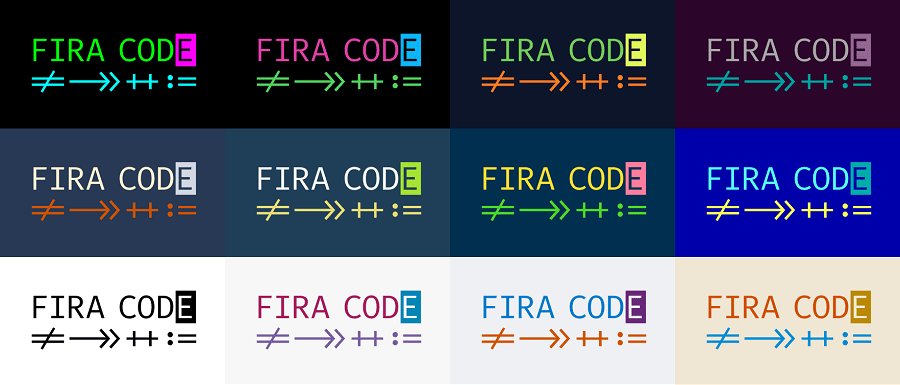
Концепция Fira Code проста: моноширинный шрифт предназначен для объединения часто используемых последовательностей из нескольких символов в одну, что сокращает время, необходимое для сканирования кода и поиска того, что вы ищете.
Например, символ «не равно» (!=) превращается в один символ «равно» с перечеркнутой косой чертой, открывающий и закрывающий символы в HTML (</) располагаются ближе друг к другу и т. д. Эти лигатуры существуют для многих языков программирования.
И это не меняет ни одного из базовых символов, как они выглядят, так что это не повлияет на ваш код. Это просто облегчает чтение!
Есть также несколько вариантов символов, поэтому вы можете настроить шрифт так, как вам нравится.
Fira Code поддерживается большинством браузеров, и вы можете увидеть, как он выглядит на реальных примерах кода, которые они предоставляют.
2. Прогги-шрифты
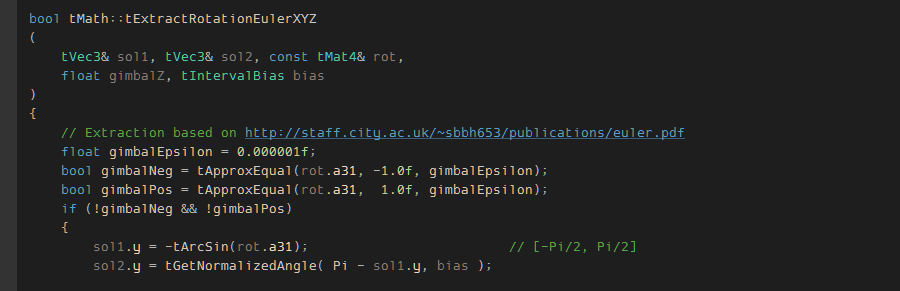
Proggy любим в кругах разработчиков за его простой, но эффективный вид, особенно для программирования на C и C++. У вас есть обычные функции, такие как ноль с косой чертой и дифференцированные буквы, а также дополнительная оптимизация, такая как звездочки с вертикальным центром и арифметические операторы, выровненные по осям.
Proggy поставляется в нескольких вариантах, включая векторную версию шрифта и более дюжины растровых версий, которые изменяют способ отображения определенных символов. Выберите тот, который вам больше всего нравится, и приступайте к кодированию!
3. ДежаВю Без Моно
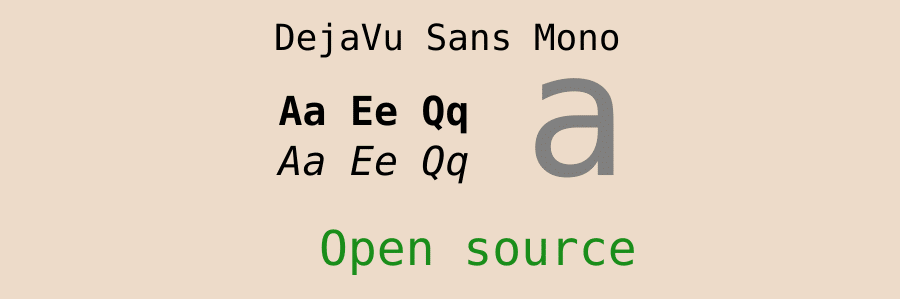
Шрифты DejaVu были разработаны для полного охвата набора символов Unicode, и хотя эта цель еще не достигнута, охват гораздо шире, чем у большинства других шрифтов.
DejaVu Sans Mono также следует этому принципу, но, конечно, это моноширинный шрифт, подходящий для разработки. Удобочитаемость и отличительные символы делают его хорошим выбором для программистов.
Поскольку шрифт является бесплатным, с открытым исходным кодом и относительно популярным, он поставляется со многими операционными системами, особенно с ОС Linux. Возможно, он уже есть на вашем компьютере, так что лучше переключиться на него, если вы не хотите заморачиваться с установкой нового шрифта.
4. Исходный код Pro
Adobe опубликовала несколько шрифтов с открытым исходным кодом в своем семействе Source Sans, и этот шрифт моноширинный и создан специально для пользовательского интерфейса. Хотя обычный вес подойдет для большинства программных приложений, при необходимости доступен ряд весов.
Хотя этот шрифт очень похож на Source Sans, в нем было несколько изменений, чтобы он лучше подходил кодерам: оптимизированные символы, ноль с точками, измененные «i», «j» и «l» и многое другое.
5. Дина
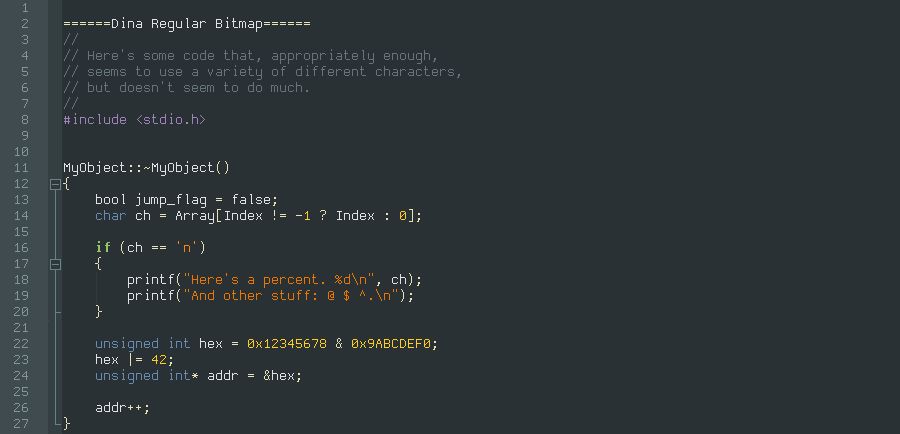
Dina — это четкий шрифт с чистым дизайном, который делает код более читабельным и вызывает меньше головной боли.
Эта версия переработана из оригинала, преобразована в TTF и обновлена для удаления артефактов. В отличие от других попыток, это, пожалуй, самая качественная и полная конвертация.
Также есть полужирная версия, если она вам нужна, и если у вас возникнут проблемы с ремастером, вы всегда можете бесплатно скачать оригинальную растровую версию.
6. Конечная остановка
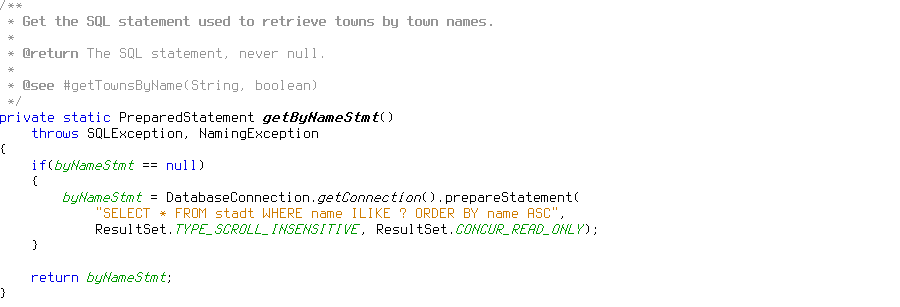
Шрифт Terminus был специально разработан для тех, кто работает в программном терминале по 8 и более часов в день. Он не повредит вашим глазам так сильно, как другие шрифты, и его очень легко установить и сканировать.
Многие разработчики, которые используют этот шрифт с момента его создания более 10 лет назад, клянутся им, поэтому, возможно, стоит его проверить.
Некоторые современные программы имеют проблемы с растровыми шрифтами, поэтому попробуйте Terminus TTF, если вы столкнулись с этой проблемой.
7. Вход
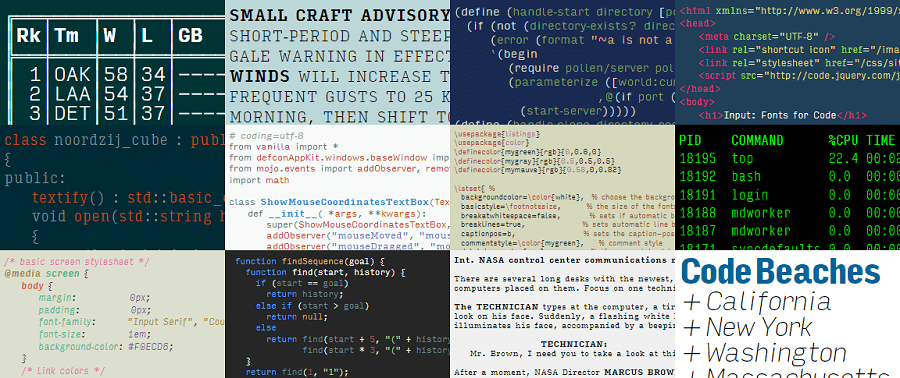
Если вам нужен сверхгибкий шрифт, доступный в нескольких стилях, который хорошо смотрится в любой ситуации, или вы постоянно сталкиваетесь с проблемами с популярными растровыми шрифтами в определенных программах, попробуйте Input.
Всего существует 168 стилей, и вы можете менять символы по умолчанию на определенные символы по своему вкусу. Вы также можете настроить межстрочный интервал. Попробуйте предварительный просмотр на их веб-сайте, чтобы увидеть, насколько он универсален.
Дизайн был вдохновлен растровыми шрифтами, популярными в сообществе, и этому процессу было уделено много внимания, включая создание пропорционального шрифта, хотя доступна и моноширинная версия.
Ввод бесплатен для частного использования, но вам потребуется лицензия для его использования в общедоступных проектах, например на веб-сайтах.
8. Взломать
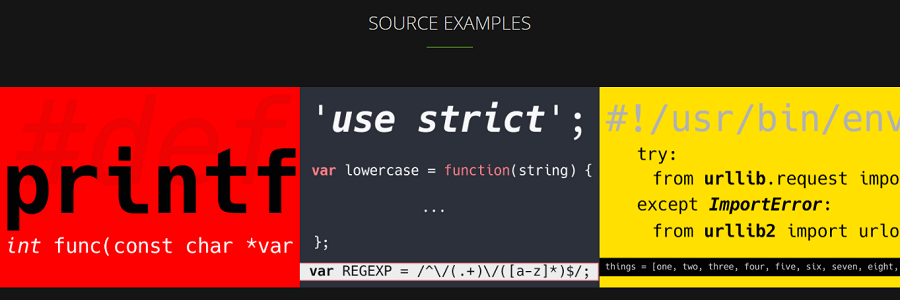
Нужен кодирующий шрифт? В Hack есть все практические функции, которые могут вам понадобиться: выделение жирным шрифтом, курсивом и их сочетанием, поддержка Powerline и тщательно продуманные символы для улучшения читаемости на экране. Нет больше прищуривания и головной боли.
Может быть сложно найти многоязычные шрифты для программирования, но Hack имеет более 1500 глифов, так что это не будет проблемой для большинства языков.
Попробуйте Font Playground, чтобы увидеть, как он выглядит на вашем любимом языке программирования, и даже сравните его с теми, которые уже установлены в вашей системе.
Наконец, попробуйте инструменты alt-hack и font-line, чтобы поменять местами альтернативные наборы символов и изменить межстрочный интервал.
9. Код Каскадия
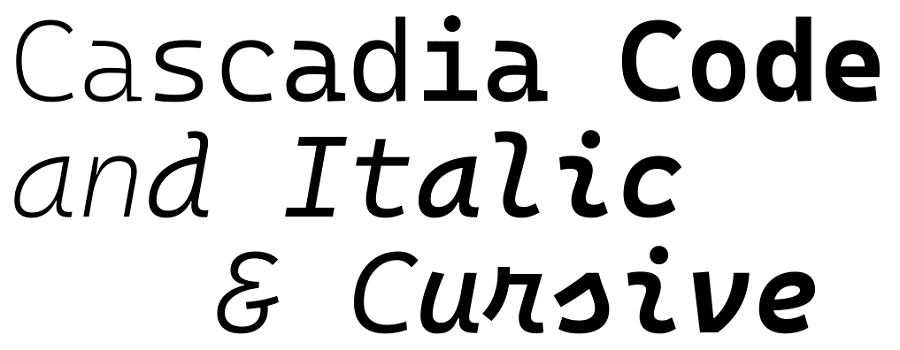
Cascadia Code — это шрифт по умолчанию для Windows Terminal и Visual Studio. Он включает шрифт по умолчанию, монохром (без лигатур), курсив и курсив, а также имеет дополнительную поддержку для встраивания символов Powerline.
Кроме того, шрифт известен своими лигатурами, как функциональными, так и стилистическими, хотя у вас есть возможность включить пакет без них. Прием среди разработчиков был неоднозначным; некоторые ненавидят его (или предпочитают старый вариант по умолчанию, Consolas), в то время как другим он нравится.
В любом случае у него открытый исходный код, поэтому вы можете попробовать его самостоятельно или загрузить Visual Studio, чтобы увидеть его в действии.
10. Моно JetBrains
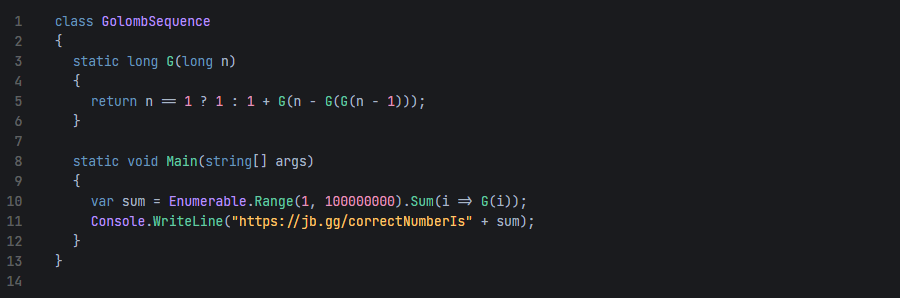
Если вы используете интегрированную среду разработки JetBrains, возможно, вы знакомы с этим шрифтом. А если нет, то вам захочется попробовать. Он создан специально для разработчиков и оптимизирован для чтения больших объемов кода.
JetBrains Mono поставляется с почти 140 лигатурами кода, 8 весами каждого с курсивом и поддержкой 145 языков. Он также имеет открытый исходный код и доступен для использования в любой личной или коммерческой ситуации.
11. Анонимный профи
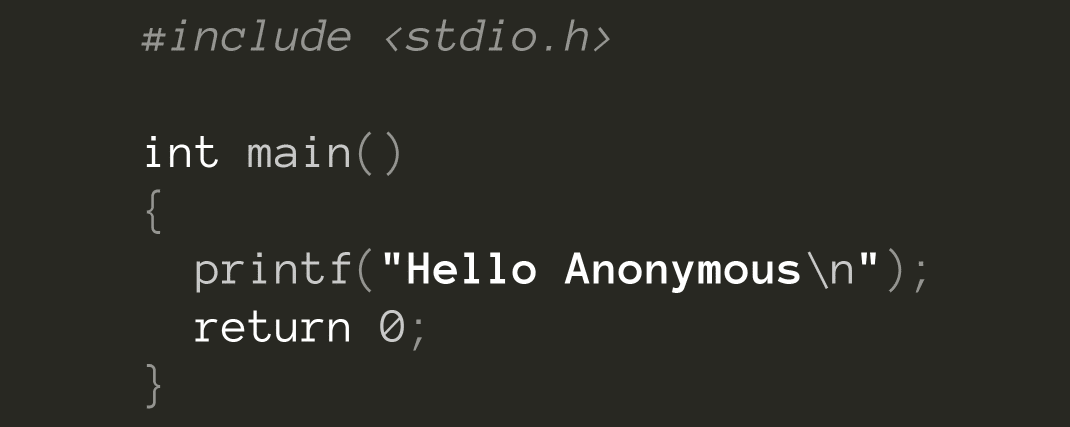
Anonymous имеет долгую историю, начавшуюся в середине 90-х, когда растровый шрифт, разработанный для Macintosh, был портирован на TrueType в 2001 году. Теперь, когда этот классический шрифт был переработан, вы получаете четыре гарнитуры фиксированной ширины, специально разработанные для программистов.
В отличие от многих других шрифтов дизайнера, этот является бесплатным по лицензии Open Font License. Если вам понравилось, посмотрите и другие его премиальные шрифты.
Платные шрифты для программирования
Не все хорошее дается бесплатно, а некоторые из лучших шрифтов для кодирования являются премиальными и платными. Хотя вместо этого вы всегда можете попробовать шрифт с открытым исходным кодом, вам может понравиться более тщательный дизайн, исследования и работа, вложенные в эти шрифты.
12. Монолиза
Устали от скучных моноширинных шрифтов, на которые некрасиво смотреть и которые вызывают напряжение глаз? Monolisa — это уникальный шрифт, который соответствует моноширинным стандартам, чтобы уменьшить усталость и при этом на него гораздо приятнее смотреть.
Помимо дизайна для лучшего чтения, Monolisa также включает символы Powerline, поддержку более 200 языков и несколько лигатур, как только пробелы, так и целые замены символов. Или вы можете отключить его, если это не ваша чашка чая.
Проверьте набор символов или игровую площадку шрифтов перед покупкой. Он включает в себя 14-дневную бесплатную пробную версию, поэтому вы можете вернуть свои деньги, если вам что-то не понравится.
13. Гинтроник
Быть программистом не означает использовать безжизненные роботизированные наборы символов, а «моноширинный» не означает «неинтересный». Gintronic читабелен и красив одновременно, с беззаботным, но техническим дизайном.
Шесть начертаний с набором курсива для каждого, поддержка различных символов и языков, и все это имеет достаточно приятный дизайн, чтобы можно было использовать его не в кодовых целях, и никто глазом не моргнул.
Gintronic доступен в нескольких пакетах, или вы можете купить ту версию, которая вам нравится. Вы также можете зарегистрироваться для получения бесплатной пробной версии, если хотите попробовать ее перед совершением.
14. Данк Моно
Многие кодовые шрифты предназначены для маленьких экранов, и многие из них не были обновлены для больших дисплеев. Данк Моно — исключение; это современный эстетичный шрифт, специально разработанный для дисплеев с высоким разрешением.
Это, конечно, не ваше традиционное моноширинное растровое изображение, но оно хорошо выполняет свою работу и при этом выглядит великолепно. Шрифт стал довольно популярным в некоторых кругах и получил в целом положительный отклик. Ознакомьтесь с рецензией создателя на его выбор дизайна, если вы хотите получить некоторое представление о процессе создания.
Личная и коммерческая лицензия существует в зависимости от того, для чего она вам нужна.
15. ПрагматаПро
Что, если вместо этого вам нужен шрифт, оптимизированный для небольших размеров экрана? PragmataPro делает свое дело. Он также не имеет межстрочного интервала, что делает его более компактным.
Его многочисленные лигатуры предназначены для работы с любым языком программирования, и в него также включено несколько забавных графических элементов.
Можно купить две версии: пакет Essential, который содержит только моноширинный шрифт без лигатуры, и полный пакет, включающий версии с моноширинным и модульным интервалом, как с лигатурами, так и без них.
Недостатком является то, что он был выпущен в 2010 году и до сих пор не достиг версии 1.0, а обновления выходят очень редко. Вы должны покупать его только в том случае, если вам нравится то, что уже есть.
Резюме
Когда ваша работа заключается в том, чтобы смотреть на экран весь день, вы обязаны выбрать шрифт, который не оставит вас с головной болью, когда рабочий день закончится. Или, может быть, вы просто ищете что-то более уникальное и интересное, чем те же самые старые шрифты, которые вы использовали более десяти лет.
Большинство людей придерживаются любого шрифта, предоставляемого их IDE, не утруждая себя его изменением, но этот шрифт не всегда является лучшим из существующих. Может потребоваться несколько попыток, чтобы найти тот, который соответствует вашим вкусам. Но поскольку большинство шрифтов для программирования бесплатны, вы можете попробовать столько, сколько захотите.